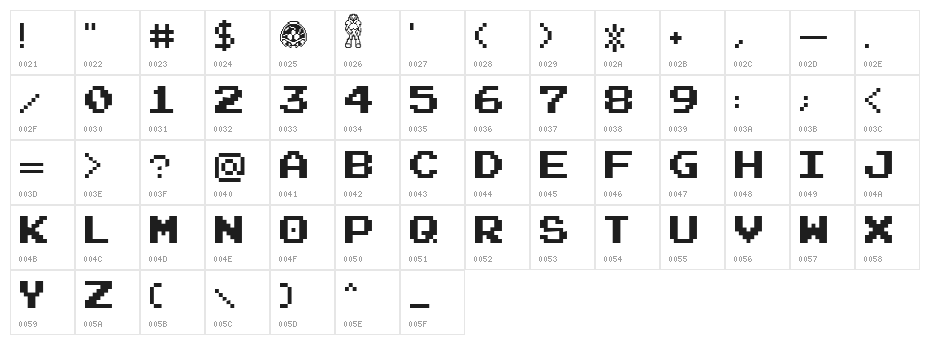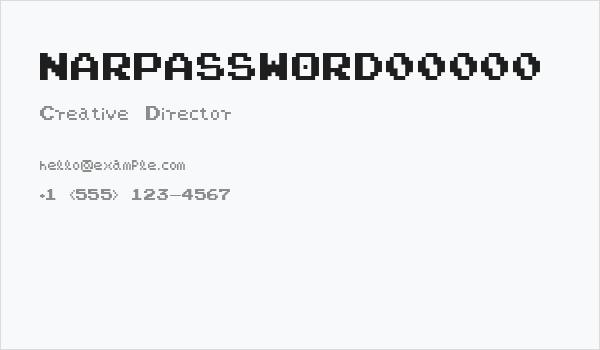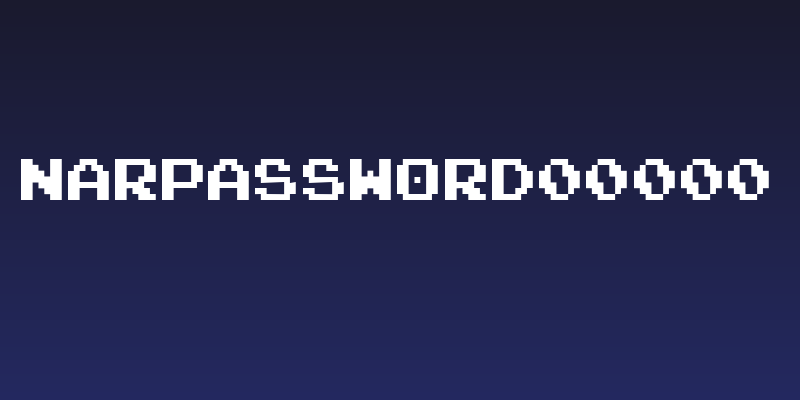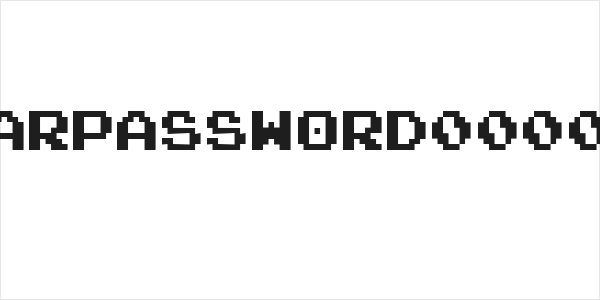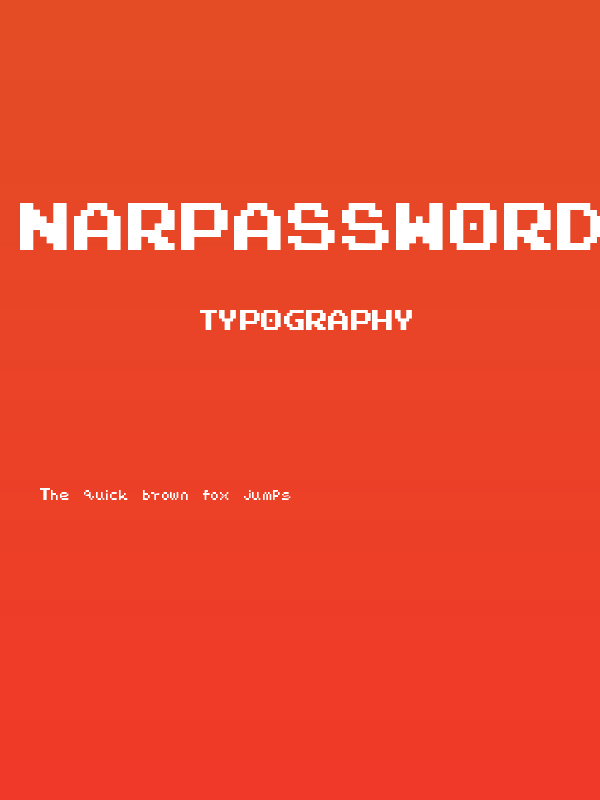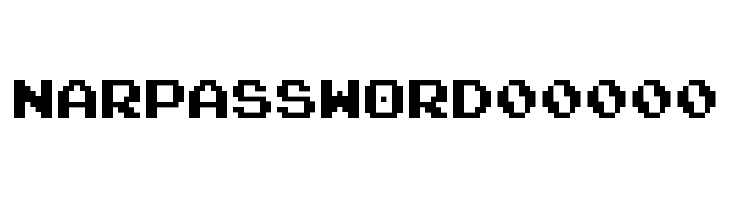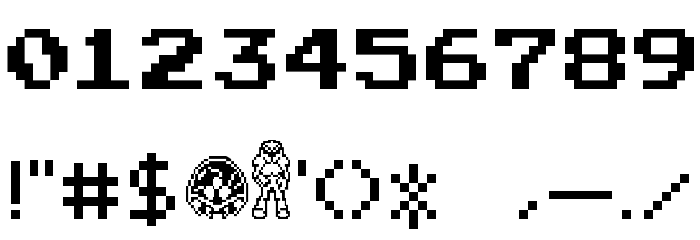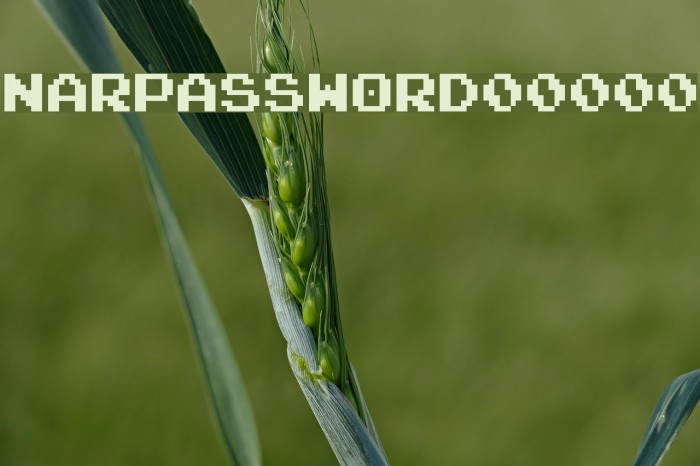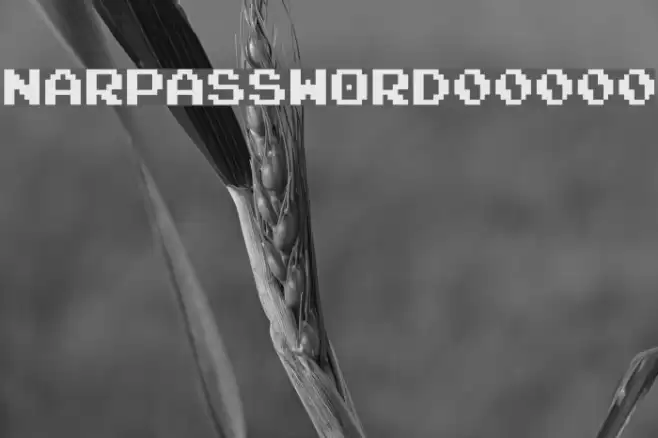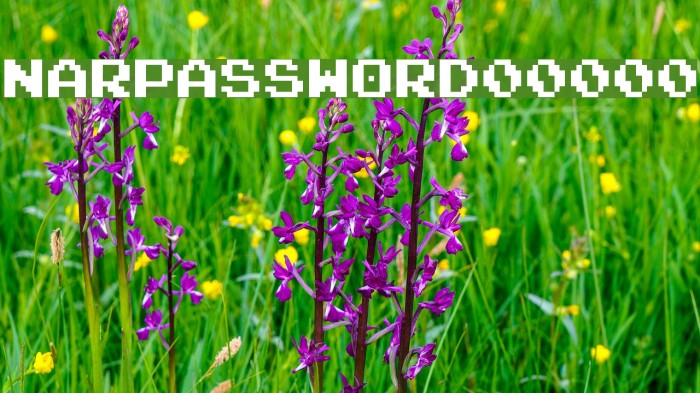
NARPASSWORD00000 Font
✎ Pixel
| Kategorien | Pixel |
| Gesamtstil | Vintage |
| Anwendungsfall | Logos, Headlines, Digital Art |
| Vorgeschlagene Projekte | Ideal for retro video game designs, digital art projects, and nostalgic branding. |